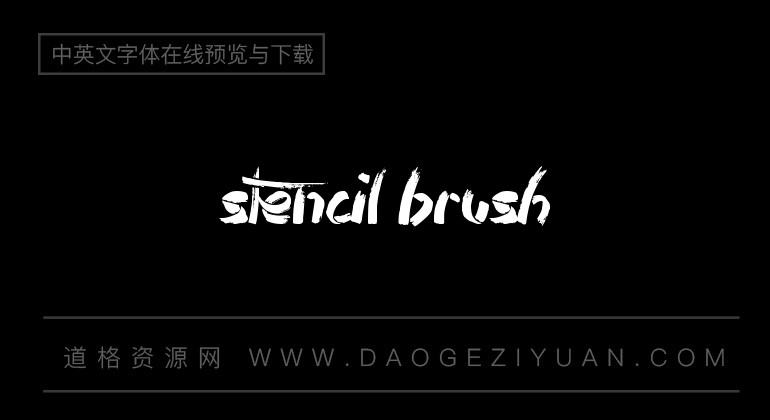
Stencil Brush 字体是一种受到绘画技巧影响的字体,它可以用于制作海报、书籍封面等,具有独特的笔触风格。它的特点是斜体字形,笔触有节奏感,具有粗细变化,可以表达出柔美的感觉。它的字体结构也很复杂,可以根据需要调整字体的大小、颜色等。Stencil Brush 字体可以满足设计师的多样化需求,为设计师提供了更多的创作可能性。内容介绍
Stencil Brush是一款非常不错的手写艺术字体,具有很好的视觉感,适合于文化类的宣传设计、商业类品牌的广告和产品包装设计以及个性化文字排版等较多场景。